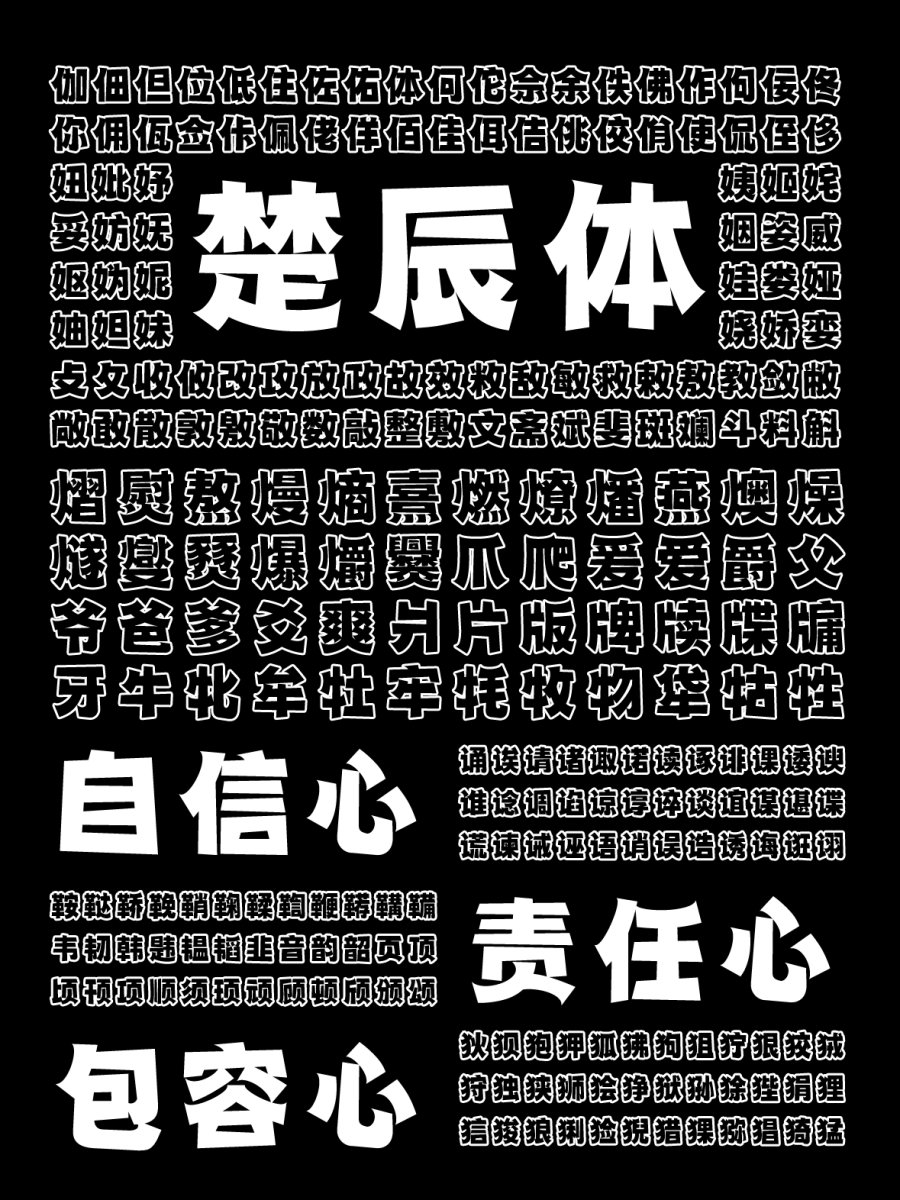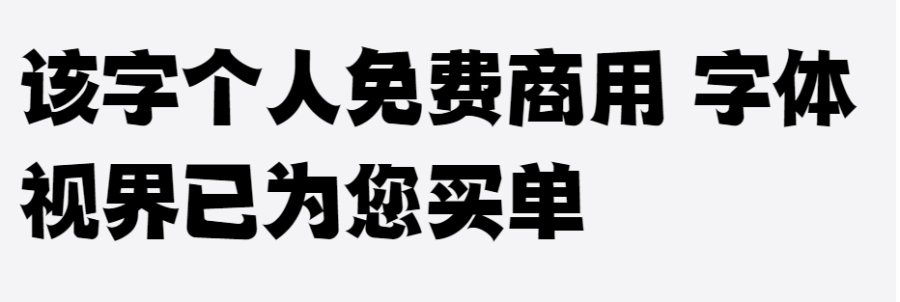
字体视界发布的个人免费商用字体——楚辰体
字体名称:楚辰体
字体类别:创意字体 黑体
“楚辰体”能在轻松时尚的氛围中体现,粗黑为字形基础,不规则的笔画,在排版时能表现跳跃的节奏感。轻快自然的特征能让标题和广告语更加醒目生动。
楚辰体
该字由著名字体设计师丞言老师耗时2年独自完成创作,由字体视界对外公开首发,供个人免费商用,企业需付费商用授权使用。
楚辰体